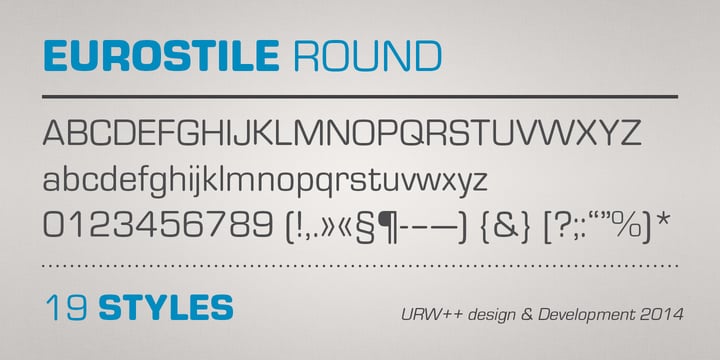
Шрифты закругленные
Есть множество интересных бесплатных шрифтов, но в этой статье собраны только самые интересные каллиграфические решения. Они пригодятся как дизайнерам, так и простым пользователям в решении повседневных задач. Шрифты Serif — часто встречаются в проектах с большим объемом текстовой информации, например, книгах, газетах и журналах. Sans serif fonts — обычно используется для создания коротких материалов, таких как титры. Рукописные шрифты — могут использоваться для всевозможных проектов, когда нужен эффект аутентичности.
Шрифты без засечек
Подбор подходящего шрифта для типографики — это трудный процесс. В сети можно найти огромное количество шрифтов в разных стилях, но беспорядочный поиск может занять не один день. Поэтому мы решили облегчить тебе задачу, и подобрали 57 трендовых шрифтов разных стилей и форм, чтобы твои творения западали в душу зрителя. В подборке ты найдешь шрифт для любого проекта. Автор шрифта Rajesh Rajput — индийский дизайнер. Он создал уже больше 10 авторских шрифтов: с засечками и круглых, классических и трехмерных.
Morganite подходит для дизайна логотипов, упаковок, веб-сайтов, печатных газет, журналов и других изданий. Использовать шрифт можно в 18 стилях, поэтому каждый дизайнер найдет, где его применить.
В году ожидается большое количество коммерческих и персональных проектов с использованием шрифтов такого типа. Теперь ты можешь придать любой иллюстрации немного цирковой магии.
The Circus Display нарисован вручную авторами 24 Design Studios. Шрифт отличается харизмой и цепляет взгляд зрителя. Смотря на такой текст, большинство невольно услышит цирковой оркестр. Arkipelago — это шрифт в рукописном стиле, буквы которого написаны мокрой кисточкой.
Автор шрифта — Nasir Udin. Несовершенный почерк придает шрифту изюминку, создает непринужденность. Он содержит дополнительные альтернативные буквы и несколько лигатур. Так твои рисунки будут выглядеть естественно, а типографика на них будет, будто написана от руки.
Tradesmith — это новый винтажный шрифт от студии Project. Он представляет собой идеальное сочетание винтажного и индустриального стилей с квадратными символами и мягкими углами. Tradesmith можно совмещать с другими шрифтами, чтобы создать аутентичный брендинг, логотипы и многое другое.
Поэтому ты можешь получить подходящий для твоего проекта характер типографики. Colus — это бесплатный шрифт дизайнера Stan Partalev. Автор был вдохновлен каменными и деревянными фактурами надписей.
Приближенный к классике стиль подходит для впечатляющих заголовков, логотипов и знаков. Colus — это профессиональный шрифт, который представлен с поддержкой многих языков, основанных на латинице и кириллице.
Фигуры в старом стиле сделают любой проект более роскошным. Colortube — это первый бесплатный цветной шрифт автора Ivan Filipov. Концепция шрифта построена в соответствии с принципами геометрии. Иван Филипов говорит, что он сделал это специально, чтобы Colortube был более привлекательным.
Шрифт поддерживает базовый набор латинских букв. Briberra — нелинейный, смелый шрифт, разработанный Sarid Ezra. Рукописные буквы содержат стилистические штрихи в альтернативных вариантах, поэтому ты можешь создать индивидуальный дизайн одежды, брендинга или других проектов.
Слова можно подчеркнуть, используя 5 стилей линии. Шрифт может использоваться для оформления заголовков, постеров разных событий, приглашений и веб-сайта, так как существует версия шрифта. Каждая буква нарисована от руки тонкой кистью на акриловой бумаге, что делает шрифт уникальным и легким к восприятию.
Cunia — это легкий шрифт без засечек с закругленными углами. Разработал шрифт Alejo Bergmann. Cunia включает в себя заглавные буквы цифры и символы. Он идеально подходит для различных целей: логотипы, значки и ярлыки, заголовки и баннеры, печатные издания и многое другое.
Приближенность к классическому стилю делает шрифт непринужденным для любого зрителя. Space Grotesk — это шрифт, созданный в году на основе шрифта Colophon Space Mono, и является его усовершенствованной модификацией. Он поддерживает латинский алфавит и символы, а его простота позволяет использовать шрифт для любых целей.
Horizon — это новый бесплатный скрипт шрифт от студии TJ Creative shop. Каждая буква нарисована вручную и имеет естественные штрихи. Шрифт подходит для поздравительных открыток, фирменных материалов, цитат, плакатов, рекламных объявлений и других проектов.